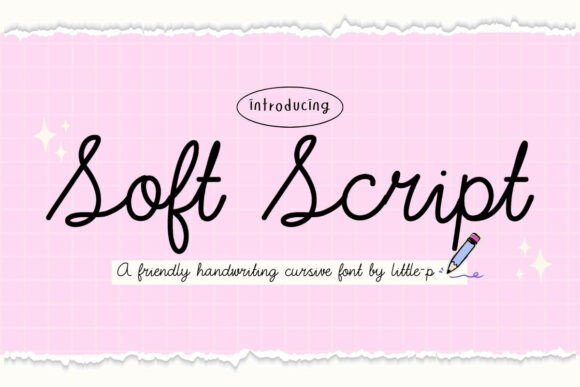
Soft Script
Découvrez la police Soft Script : une touche douce et authentique pour vos projets créatifs
Bring a gentle, personal touch to your projects with the Soft Script font, a friendly handwriting cursive typeface that feels as natural as a handwritten note. Avec son flux monoline lisse et ses boucles élégantes, cette police d'écriture manuscrite capte un charme effortless et une convivialité irrésistibles. Que vous travailliez sur un blog lifestyle, un tutoriel DIY ou du contenu social media léger, Soft Script saura apporter une touche chaleureuse et professionnelle à vos créations.
Idéale pour des applications variées
Cette police Soft Script se distingue par sa lisibilité, même en petite taille, grâce à ses traits cursive soignés. Elle est parfaite pour :
- Des projets créatifs : cartes de vœux, autocollants, printables, et illustrations manuscrites.
- Des supports éducatifs : fiches pédagogiques, planners, et designs pour enfants.
- Des marques féminines ou des journaux personnalisés où l'authenticité prime.
Combinaisons esthétiques pour un impact visuel
Pour renforcer son côté accueillant, associez Soft Script à des palettes pastel douces ou des illustrations dessinées à la main. Cette combinaison crée un contraste harmonieux, idéal pour des graphismes sociaux ou des projets DIY où la chaleur humaine est essentielle.